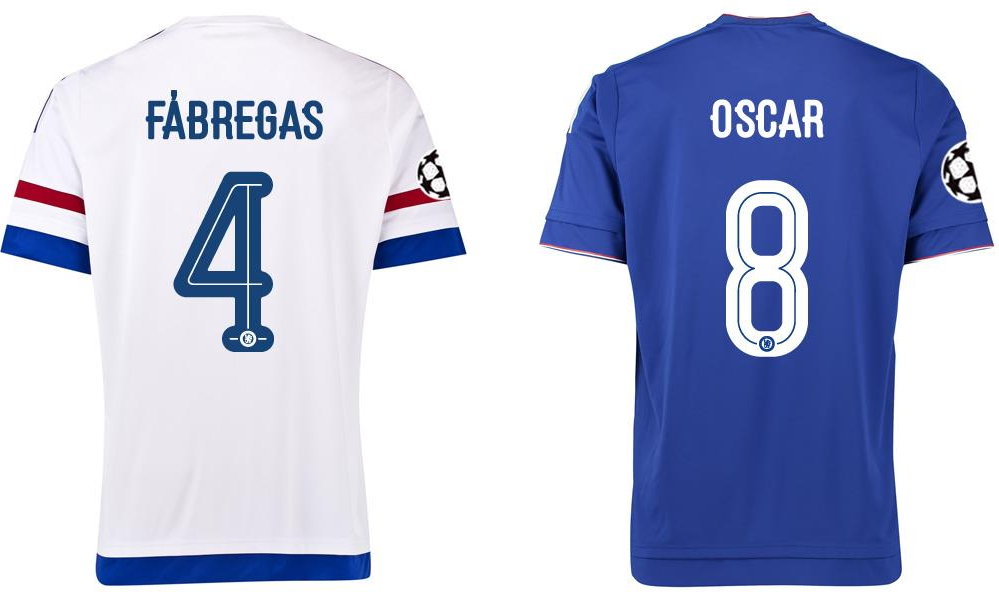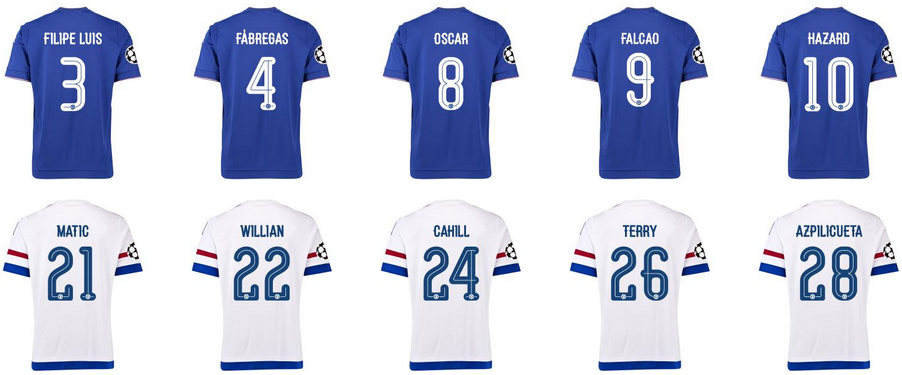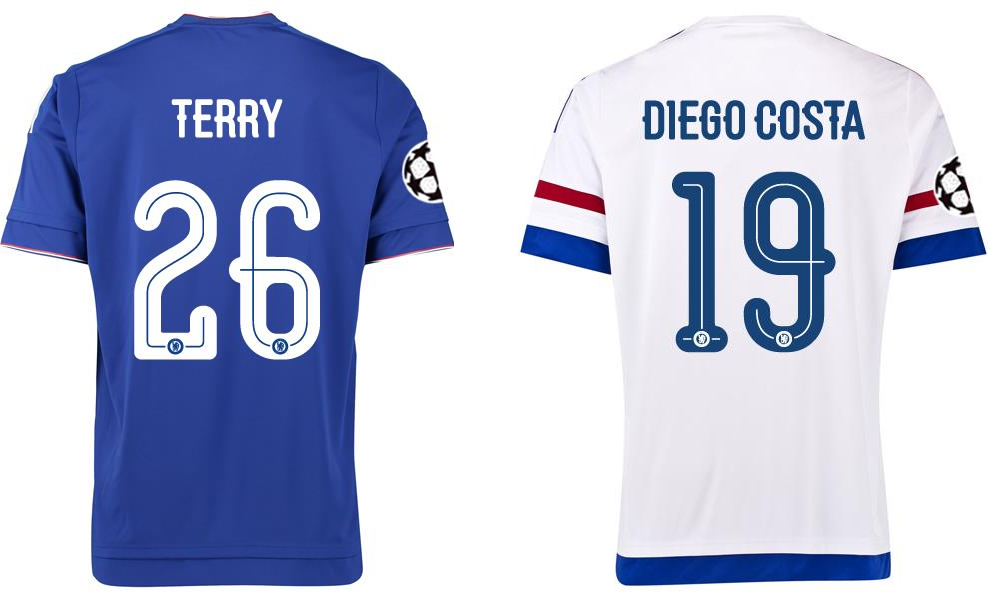
先日、2015-16シーズンに向けた新しいユニフォームを発表したチェルシー。新たに胸スポンサーとなった「YOKOHAMA TYRES」のロゴが新鮮なデザインとなっている。
そのチェルシーの新ユニフォームのフォントがなかなか面白い感じになっていた。
ご存知のとおり、プレミアリーグではChris Kay社によるフォントが全チーム共通となっているが、カップ戦では独自のフォントを使うことが可能。これらのフォントはCLなどで使用されると予想される。
丸みを帯びたデザインとなっており、番号の中央にはラインが引かれているほか、下部にはクラブロゴが鎮座。6や9などの数字に見られる“出っ張り”が特徴的だ。名前のローマ字も所々“出っ張っている”。
この新たなフォントは2000年代中頃のUmbro時代のものからインスピレーションを受けているとも海外では伝えられている。
確かに面影がある。チェルシーがカップ戦を戦う際には、背中に注目してみるのもいいかもしれない。